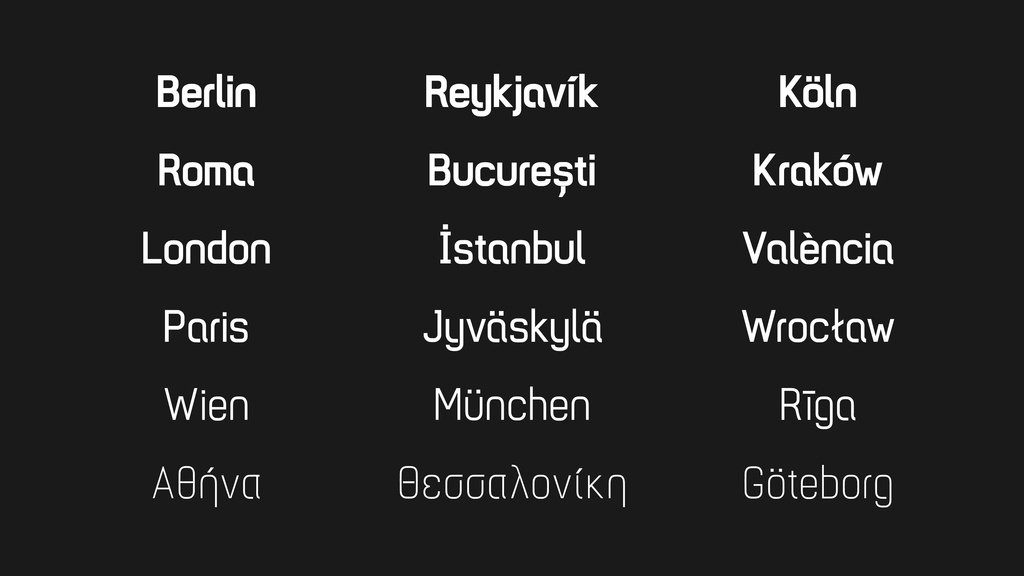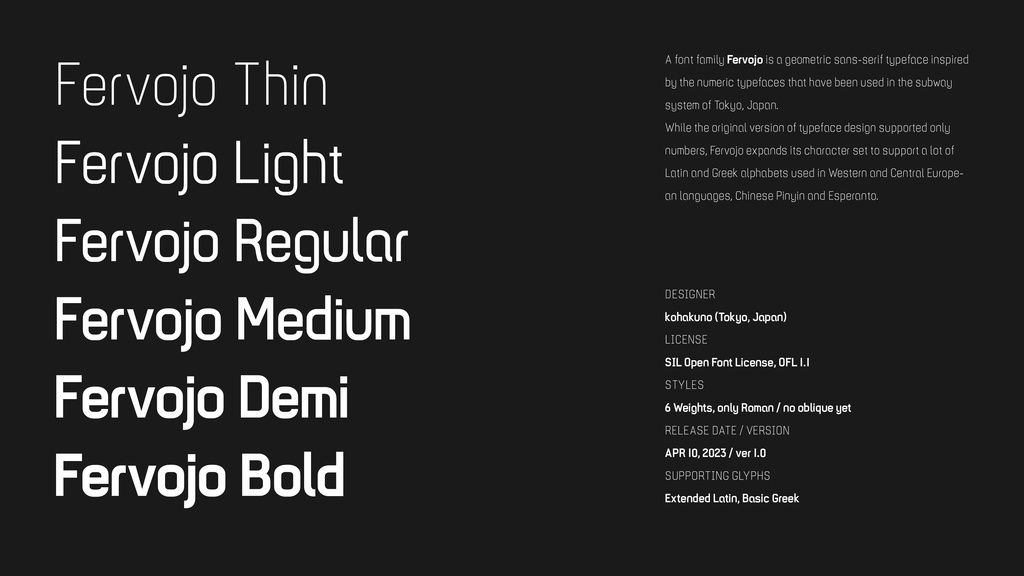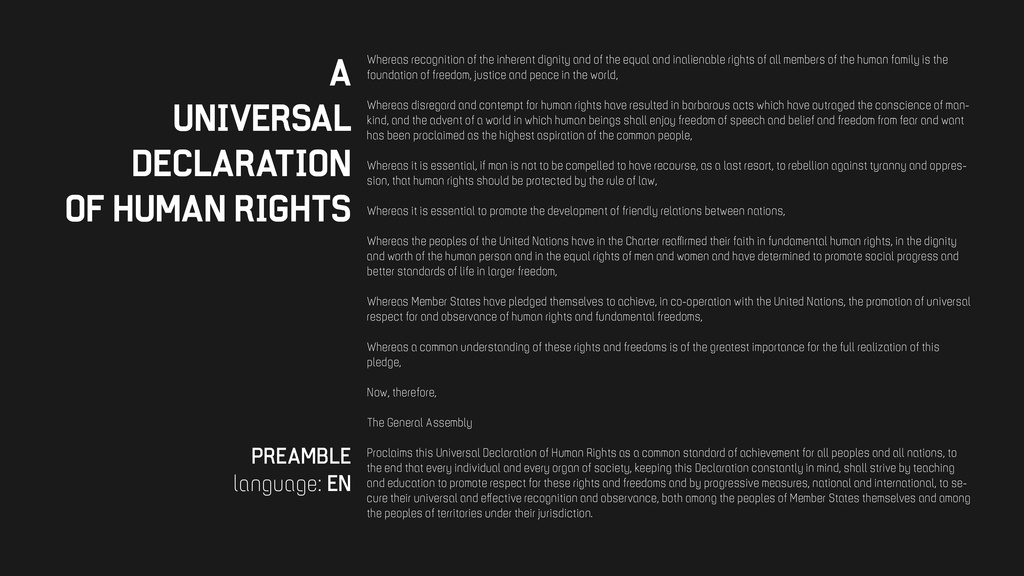
【フリーフォント】Fervojo
■書体概要 「Fervojo(フェルボヨ)」はジオメトリック・スタイルのサンセリフフォントです。 ThinからBoldまでの6ウエイトで構成されたフォントファミリで、ラテン文字アルファベットとギリシャ文字アルファベットを搭載しています。 東京の地下鉄で車両番号の表記に使われている数字書体(「営団数字」とも呼ばれているそうです)にインスパイアされて制作を進めました。 字形デザインの詳細は、私のBehanceアカウントをご確認ください。 ■ライセンス SILオープンフォントライセンスでの提供です。商用・非商用問わずご自由にご利用いただけます。 ■About This Fonts A font family Fervojo is a geometric sans-serif typeface inspired by the numeric typefaces that have been used in the subway system of Tokyo, Japan (the original numeric typeface is also called “Eidan-Numbers” or “Eidan-Typeface”). The Fervojo font family has 6 weights (Thin to Bold), and they support the alphabets of the Latin Extended and the Greek Basic. If you want to check more information and detail of the type design, please visit my Behance post. ■About License This font family is published under the SIL Open Font license 1.1 (OFL 1.1). === APR 10, 2023 [ver.1.0] 公開 (c) 2023 kohakuno All Rights Reserved.